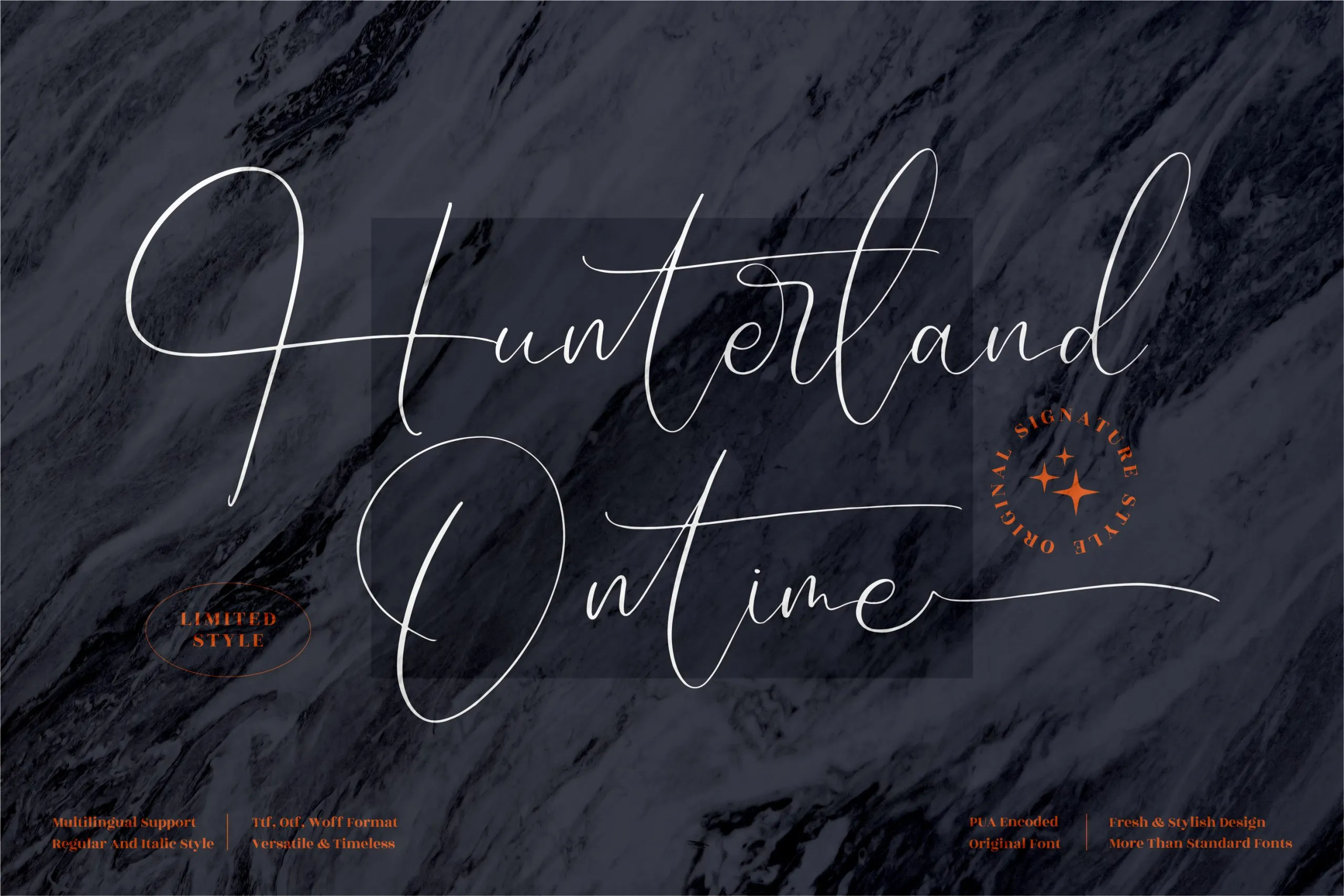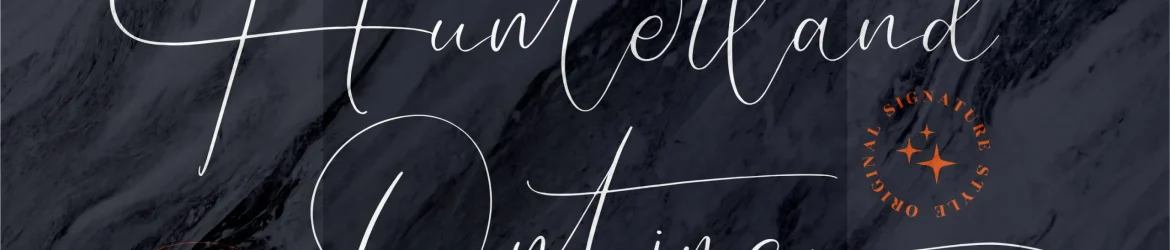
Hunterland Ontime Font – Download Grátis
A Hunterland Ontime Font é uma elegante assinatura que surgiu da Perspectype Studio. Especialmente projetada para se destacar em qualquer projeto, essa fonte premium combina elegância com estilo, sendo perfeita para uma variedade de ambientes e aplicações. Da criação de logomarcas e identidades empresariais aos designs de prateleira, embalagens de produtos e até mesmo itens pessoais como bandejas de café ou sacolas de shopping, ela encaixa-se em todos esses perfis sem comprometer a qualidade do trabalho. A Hunterland Ontime Font é um trunfo inigualável para quem procura criar designs personalizados com o toque de uma assinatura única. Seja para etiquetas de produtos ou mesmo camisas personalizadas, seu design elegante e moderno será o ponto focal que tornará qualquer projeto único. Não importa qual seja a sua necessidade criativa – este fonte é uma solução perfeita.